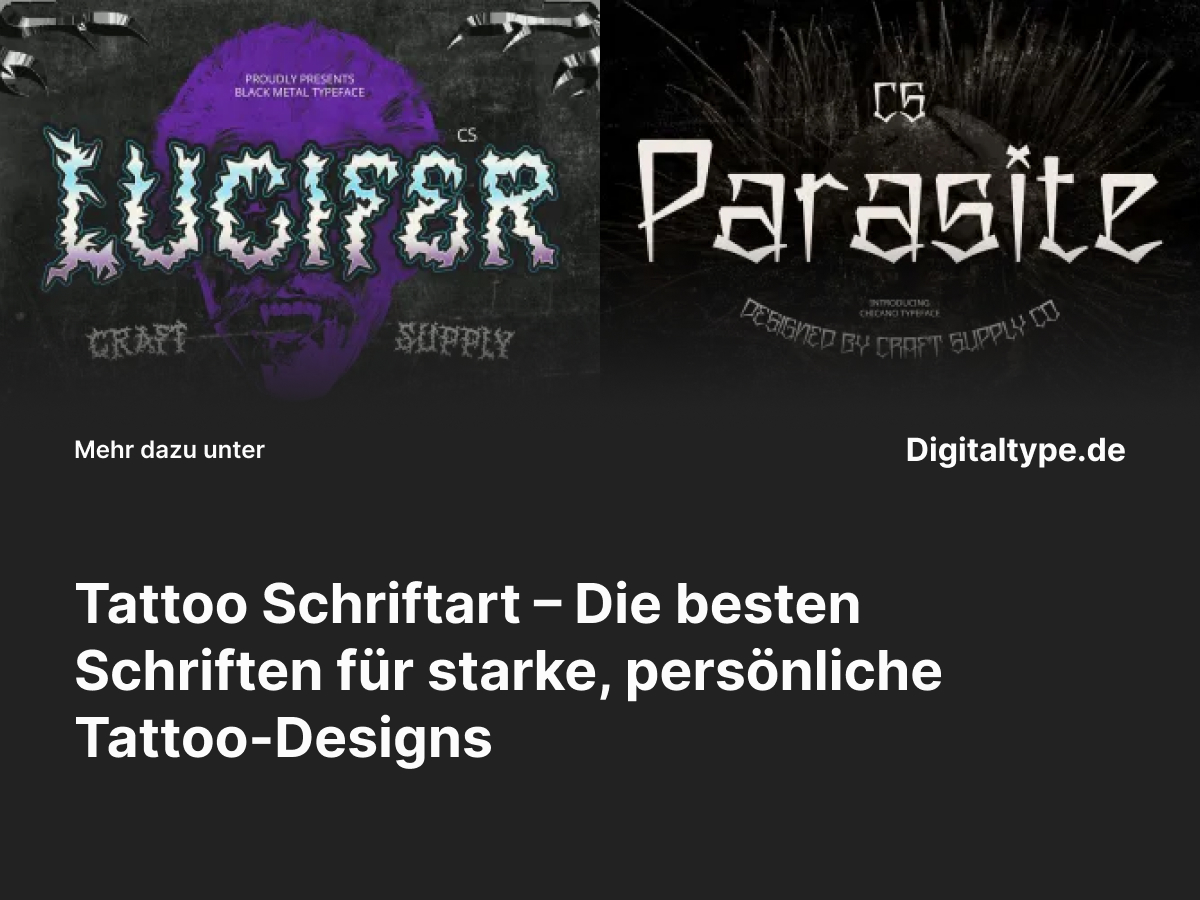
Eine Tattoo Schriftart ist mehr als nur Buchstaben auf der Haut – sie ist ein Ausdruck von Identität, Emotion und Individualität. Ob ein bedeutungsvolles Zitat, ein Name oder ein spirituelles Symbol: Die Wahl der richtigen Schrift bestimmt, wie kraftvoll und zeitlos dein Tattoo wirkt. In diesem Artikel erfährst du, welche Tattoo-Schriftarten besonders beliebt sind, welche Stile zu welchen Motiven passen und welche modernen Alternativen du für dein Design ausprobieren solltest.
Was ist eine Tattoo Schriftart?
Eine Tattoo Schriftart ist speziell dafür konzipiert, Emotion und Ästhetik zu verbinden. Sie muss sowohl auf der Haut als auch in digitaler Form stark wirken. Typisch sind klare, kontrastreiche Linien, oft inspiriert von Blackletter-, Chicano– oder Gothic-Typografie. Diese Schriftstile betonen Stärke, Ausdruck und Charakter – ideal für Designs, die Bedeutung tragen.
Tattoo-Schriften werden häufig in folgenden Stilen verwendet:
- Blackletter: Traditionell, königlich und mächtig – perfekt für klassische oder religiöse Tattoos.
- Chicano: Elegant, schwungvoll und emotional – ideal für Namen, Sprüche oder Street-inspirierte Designs.
- Modern Gothic: Eine Mischung aus Tradition und moderner Typografie – für minimalistische, aber eindrucksvolle Tattoos.
Wann du eine Tattoo Schriftart verwenden solltest
- ✔️ Für Tattoos mit bedeutungsvollen Zitaten oder Lebensmottos.
- ✔️ Wenn du Stärke, Glauben oder Rebellion ausdrücken willst.
- ✔️ In Kombination mit Symbolen wie Kreuzen, Flügeln, Rosen oder Totenköpfen.
- ✔️ Für Namen oder Erinnerungen, die dauerhaft in Erinnerung bleiben sollen.
Die passende Tattoo Schriftart verleiht deinem Design Persönlichkeit und Tiefe. Wähle den Stil, der zu deiner Geschichte passt – ob elegant, rebellisch oder mystisch.
Die 6 besten Tattoo-Schriftarten für einzigartige Designs
Hier sind sechs ausgewählte Tattoo-Schriftarten, die sowohl künstlerisch als auch professionell gestaltet sind. Jede Schrift trägt eine eigene Stimmung – von dunkler Mystik bis zu handgemachter Authentizität.
1. CS Lucifer Black Metal Font
CS Lucifer ist eine markante Tattoo Schriftart im Stil des Black Metal. Ihre kantigen, scharfen Formen erzeugen eine dunkle, kraftvolle Aura. Ideal für Tattoos, die Stärke, Rebellion oder spirituelle Energie ausdrücken. Besonders beliebt in Rock-, Metal- oder Gothic-inspirierten Designs.
2. CS Parasite Chicano Graffiti Font
Diese Schrift kombiniert Chicano-Stil mit urbaner Graffiti-Ästhetik. Die geschwungenen Linien und dekorativen Details verleihen ihr einen emotionalen, lebendigen Charakter. Perfekt für persönliche Schriftzüge, Familiennamen oder inspirierende Worte mit urbanem Flair.
3. CS Hastings Blackletter Font
CS Hastings ist eine elegante Blackletter-Schrift mit feinen Proportionen und klassischem Charakter. Diese Tattoo Schriftart eignet sich hervorragend für detailreiche Tattoos mit traditionellem Look – von gotischen Zitaten bis zu religiösen Symbolen.
4. CS Rolins Blackletter Font
CS Rolins ist stark, kontrastreich und selbstbewusst. Ihre dramatischen Buchstabenformen verleihen jedem Tattoo Autorität und Ausdruckskraft. Besonders beliebt für Schriftzüge auf Brust, Rücken oder Unterarm – sie wirkt wie ein Symbol für Mut und Beständigkeit.
5. CS Mirage Blackletter Font
CS Mirage verbindet dekorative Details mit solider Struktur. Diese Schrift bringt Tiefe und Eleganz in jedes Tattoo. Sie ist perfekt für kunstvolle Schriftzüge, kombiniert mit Ornamenten oder Symbolen, die Spiritualität oder Emotion ausdrücken.
6. CS Rebelion Blackletter Font
Wie der Name schon sagt, steht CS Rebelion für Stärke, Freiheit und Individualität. Diese Schrift wirkt markant und rebellisch – perfekt für Menschen, die mit ihrem Tattoo ein Statement setzen wollen. Ob groß oder klein, sie zieht garantiert Aufmerksamkeit auf sich.
Tipps für die perfekte Tattoo Schrift
- 1. Teste verschiedene Größen: Nicht jede Schrift sieht in kleiner Größe gut aus – prüfe Lesbarkeit vor dem Stechen.
- 2. Vermeide zu viele Schnörkel: Filigrane Linien können mit der Zeit verschwimmen – besser klare Strukturen wählen.
- 3. Achte auf Kontrast: Dunkle, kräftige Linien wirken langlebiger und sind optisch stabiler.
- 4. Stimme Schrift und Bedeutung ab: Wähle eine Schrift, die Emotion und Inhalt deines Tattoos unterstützt.
Fazit: Tattoo Schriftarten mit Charakter und Tiefe
Eine Tattoo Schriftart ist mehr als nur Design – sie ist Symbol für Persönlichkeit, Erinnerung und Überzeugung. Mit der richtigen Schrift kannst du deinem Tattoo Ausdruck und Stärke verleihen, egal ob du Tradition oder Moderne bevorzugst.
Die oben vorgestellten Schriftarten vereinen Handwerkskunst, Stil und Emotion – ideal für jeden, der ein Tattoo mit Bedeutung plant. Ob du dunkle Blackletter-Looks oder kunstvolle Chicano-Styles bevorzugst: Deine Schrift erzählt deine Geschichte.